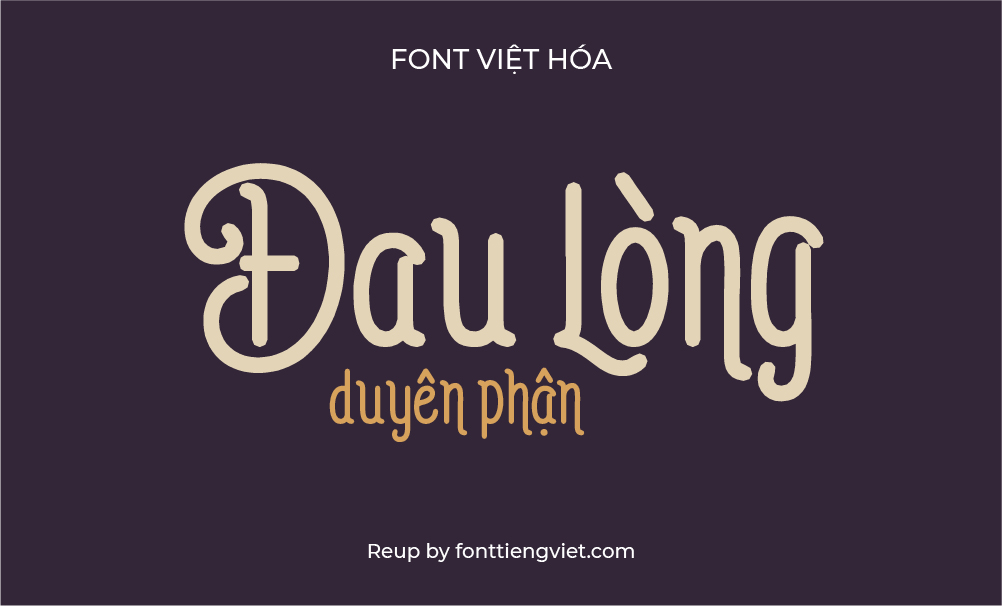
Font Việt Hóa iCiel Auther Typeface – Vẻ Đẹp Cổ Điển Cho Thiết Kế Việt
Giới thiệu về Font Việt Hóa iCiel Auther Typeface
Trong thế giới đồ họa hiện đại, việc lựa chọn một Font Chữ phù hợp đóng vai trò quyết định đến tính thẩm mỹ của sản phẩm. Font Việt Hóa iCiel Auther Typeface là một sự kết hợp hoàn hảo giữa nét vẽ tay mộc mạc và phong cách Typography cổ điển. Được lấy cảm hứng từ những bảng hiệu vintage và nghệ thuật viết chữ thế kỷ trước, bộ font này mang đến cảm giác hoài cổ nhưng vẫn rất tinh tế. Phiên bản iCiel Auther đã được tối ưu hóa hoàn toàn cho tiếng Việt, giúp các bạn học sinh và nhà thiết kế dễ dàng sử dụng trong các bài thuyết trình, thiệp mời hay bìa sách mà không lo lỗi hiển thị dấu.
Đặc điểm nổi bật của iCiel Auther Typeface
Phong cách thiết kế độc đáo
Font Việt Hóa iCiel Auther Typeface sở hữu các đường nét uyển chuyển, mạnh mẽ nhưng không kém phần mềm mại. Điểm đặc biệt của bộ font này là các ký tự thay thế (alternates) và các đường gạch nối (ligatures) vô cùng phong phú. Điều này cho phép người dùng sáng tạo ra những tiêu đề ấn tượng, có chiều sâu nghệ thuật cao. Đối với các dự án trường học, font chữ này giúp tôn vinh vẻ đẹp truyền thống và sự chỉn chu trong từng con chữ.
Tính ứng dụng linh hoạt trong đời sống
Không chỉ giới hạn trong thiết kế chuyên nghiệp, bộ font này còn rất phù hợp cho việc trang trí bài tập lớn, làm nhãn vở hay thiết kế đồng phục lớp. Nhờ định dạng linh hoạt, bạn có thể sử dụng iCiel Auther trên nhiều phần mềm khác nhau từ Office đến Adobe. Sự chỉn chu trong cách việt hóa giúp các dấu thanh nằm đúng vị trí, tạo nên sự cân đối tuyệt vời cho văn bản.